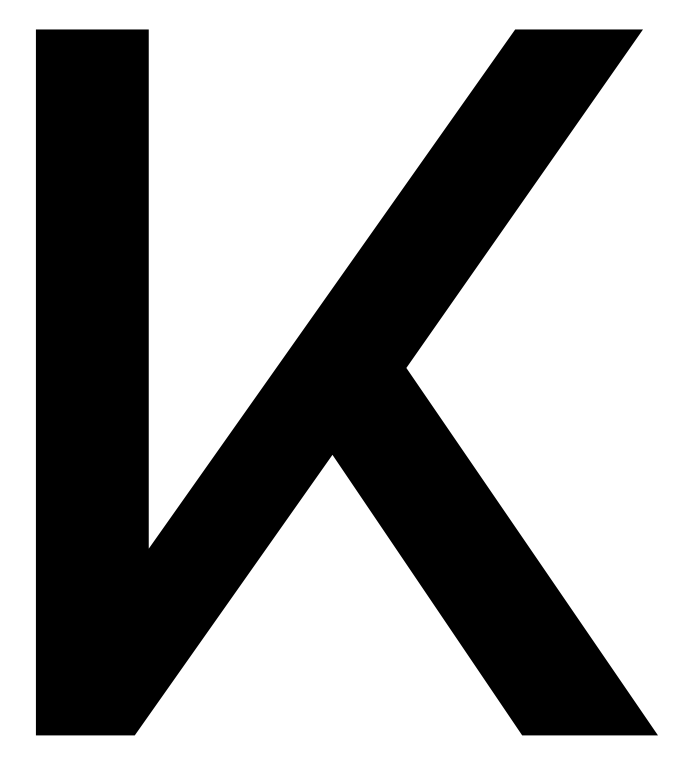
Schriften mit „Haken“-K
Haken-K
Ich bin auf der Suche nach Schriften mit einem Versal-K, dessen Aufstrich auf Höhe der Grundlinie an den Stamm anschließt. Folgende Schriften habe ich bereits gefunden:
Aftika von Deepak Dogra, Graphite
Alergia Remix von Mateusz Machalski, Borutta/Capitalics
Baradig von Bayu Noor Witarsa, Asenbayu
Cabinor von BeeType via Creative Fabrica
Criteria von Connary Fagen, Connary Fagen Fonts
Cukier von Mateusz Machalski, Borutta/Capitalics
Differentura von Abstrkt
Fanatrike von Nan Design via Creative Fabrica
Felk von BeeType via Creative Fabrica
Gatte Modern von Moch Fitrah Hidayat, Fitrah Type
Gottora von Artiveko Studio
Graphito von Evin Tony, FoxType
Hyakinthos von A Christie via Creative Fabrica
Kavo Sans von Vladimir Fedotov und Plamen Petrov, VP Creative Shop
Kindel von VP Fonts via Creative Market
Lorenza von Abdul Malik Wisnu, Almarkha Type
Lydia Sans von João Cracel, Craceltype
Lucifer Sans von Daniel Brokstad
Mismo von EyeCone via FontBundles.net
Monoset von Leonhard Katschner, Brave Type
Neo Grotesk von Arne Freytag, Fontador
Noreva von Roomspace via Creative Fabrica
Partakes von Nan Design via Creative Fabrica
Qioba von Ardyana Putra, Ardyanatypes
Radikal von Nico Inosanto, Nootype
Solen von Pavel Larin, Larin Type Co
Strouse von Huntype via Creative Fabrica
Trakya Round von Bülent Yüksel
Trakya Sans von Bülent Yüksel
Wright von Diego Maldonado, Latinotype
Zupra Sans von Ole Schäfer, Primetype
Ich hab einfach dein K bei WFI und WTF verwendet und mir passende anzeigen lassen. -D
Ich habe versucht, alle Schriften, die Diwarnai gefunden hat, in die Liste aufzunehmen.
Folgende konnte ich nicht finden: The Brittany Sans, Deounder, Quick-Regular. Die FV Granada ist nur für personal-use; der Link zum Studio Floris führte ins Leere.
Meine Entscheidung ist gefallen. Es ist die Neo Grotesk von Arne Freytag (Fontador) geworden.
Sollten noch Sichtungen eingereicht werden, kann die Liste gerne weiterführen.
Die Radikal war mir schon länger bekannt. Auf die Schnelle finde ich als Benutzer die Achse des Guten (achgut). IIRC waren noch einige andere konservative Medien mit dieser Schrift?
Das ist mir damals vor vielen Jahren aufgefallen: Konservativ, also politisch Mitte, und „Radikal“. Ich vermute eine Anlehnung an die Neuzeit Grotesk in der BILD. Welt-Online hat mit der FF-Mark auch eine an die Neuzeit Grotesk angelehnte Schrift.